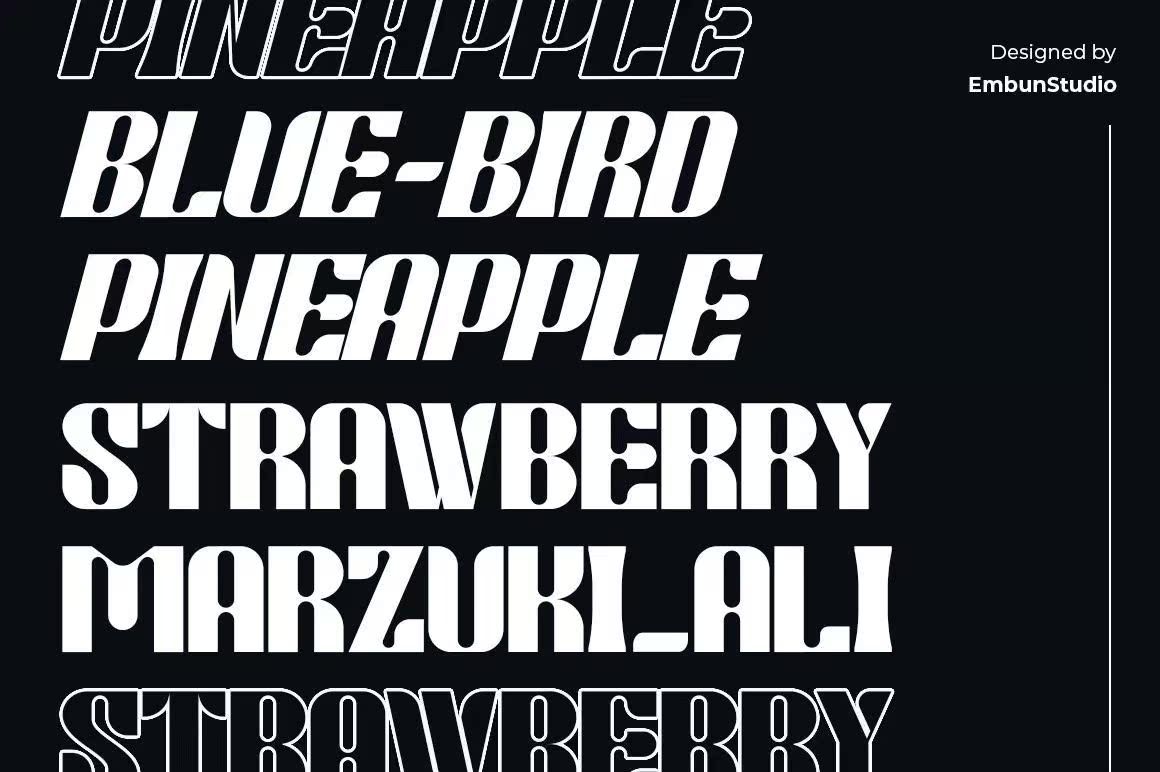
让我介绍我的新字体,thinktypeface,NewTypefacet给您提供新体验的UringuseSansFont,Classic和Futuristic None Font with 4 Style Regular,Bold,Regularic,Bold Italic让我介绍我的新字体,thinktypeface,NewTypefacet给您提供新体验的UringuseSansFont,Classic和Futuristic None Font with 4 Style Regular,Bold,Regularistic,Bold Italic